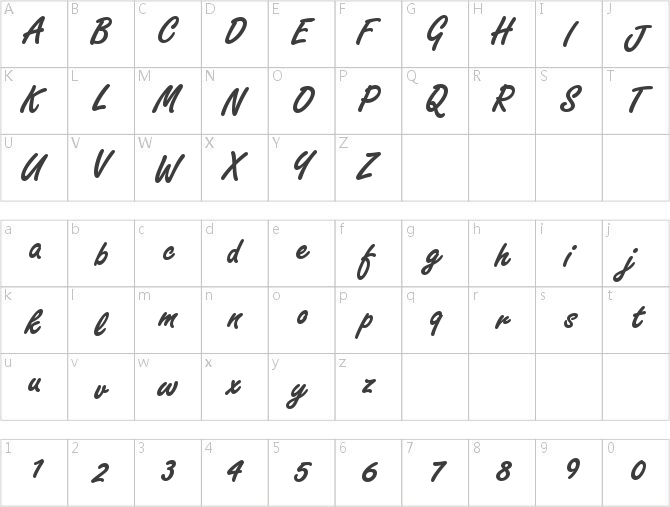
FreestyleScrDEE-Bold 詳情頁(yè)
FreestyleScrDEE-Bold字體字庫(kù)是一款讓人賞心悅目、百看不厭的英文字體,適合各類廣告和產(chǎn)品包裝設(shè)計(jì)應(yīng)用,字體大小0.05MB,格式為ttf字體,上傳用戶是多拉MO,作者/版權(quán)方為未知